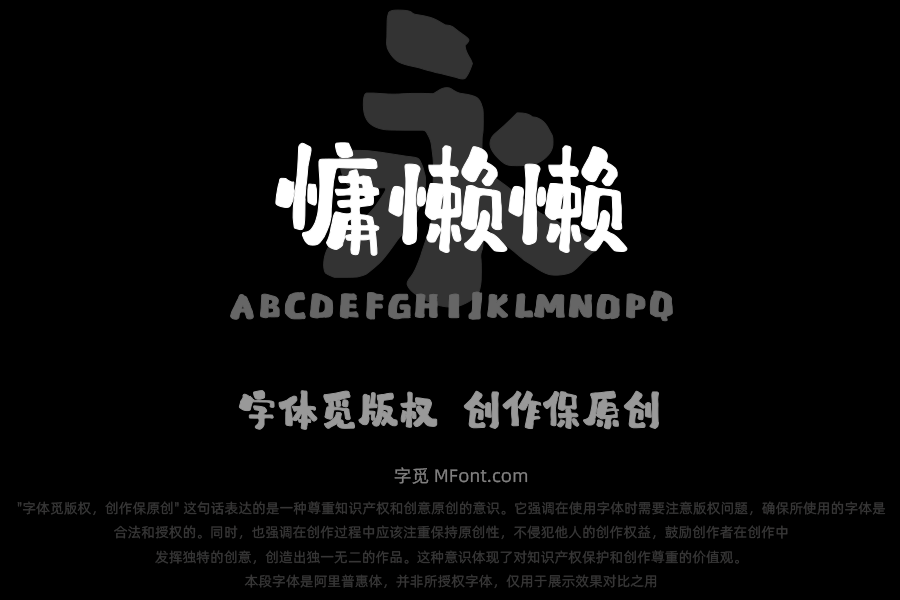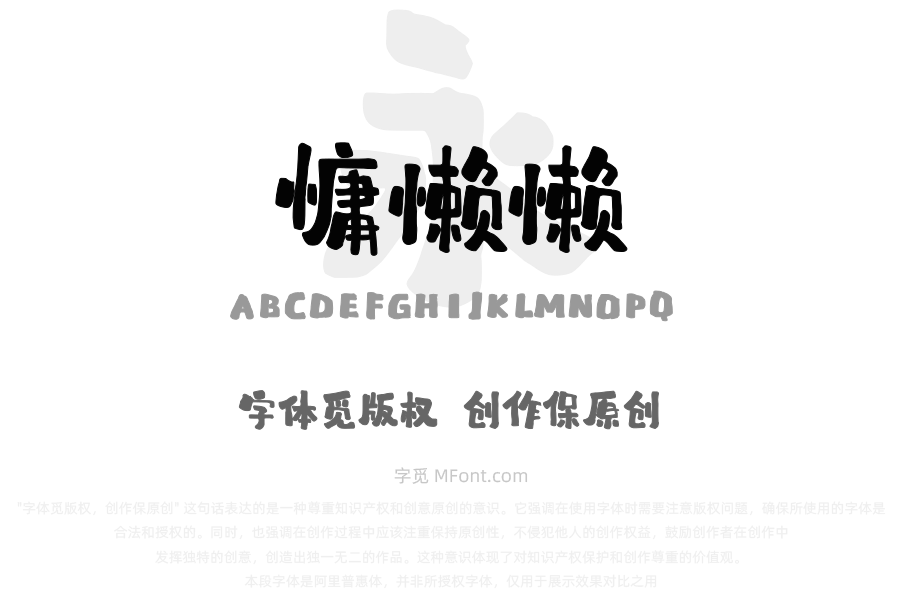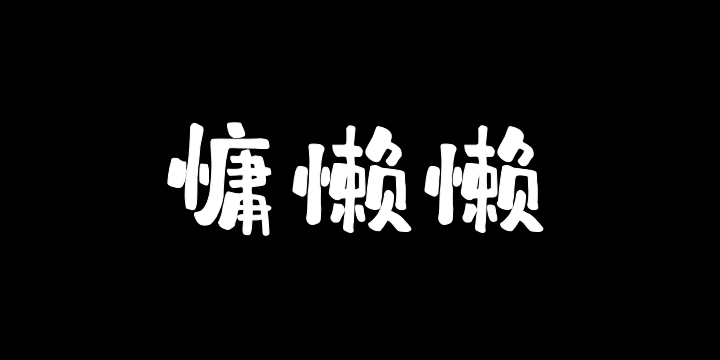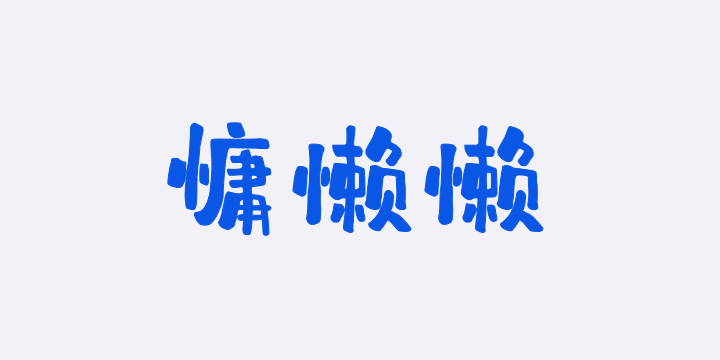
字潮慵懒懒
字潮字库
关于字潮慵懒懒字体字库信息
字体全名: 字潮慵懒懒
铸字厂: 字潮字库
设计师: 丁道华
字体简介: 字潮慵懒懒笔画有力,强调线条的厚重感和冲击力,每个字的起笔和收笔都带有明显的张力,呈现出一种动态的视觉效果。这种设计避免了机械化的呆板,反而融入手写的随性,笔画间有细微的不规则感,增添了自然洒脱的气息。